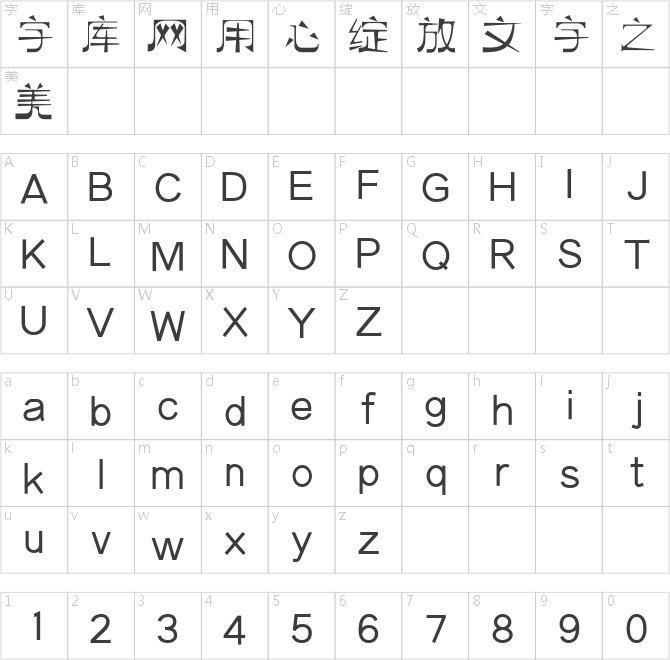
字體名稱: 逐浪萌芽字
逐浪萌芽字
逐浪萌芽字介紹
一款參照借鑒近代中國共產黨《萌芽》月刊的藝術字體。
源自五四運動文化,力求體現近代文藝風。
字體線條呈現外方內圓格局,有尖銳的外角、三角部件,而內部空間則呈現圓形切割效果。
這體現了五四、清末民初,在工業革命思維沖擊下,一代文化人對于中國漢字的探索。
又似布爾什維克人的工人、工業文化在漢字下的體現。
尖銳、銳角三角形的部件,從中體現了上進、革命、進擊。
結字扁形,即左右寬度大于上下高度。
• 1.外角采用尖角,內角采用弧角
• 2.是一個抽象的孤形字。
• 3.試圖創造上個世紀30年代“左聯”的手寫字體風格,該風格是用于出版物出版,簡樸又不失藝術性。
• 4.多弧形、多三角形。
• 5.整體偏矮寬方正型,非常規字體,異型字居多
• 6.筆畫粗細對比明顯,角的筆畫相對橫豎線要粗
• 7.豎線筆畫下端粗上端細,橫線筆畫左邊粗右邊細
• 8.外角整體偏方形,內角整體偏圓形的創意字體
• 9.整體風格硬朗纖細